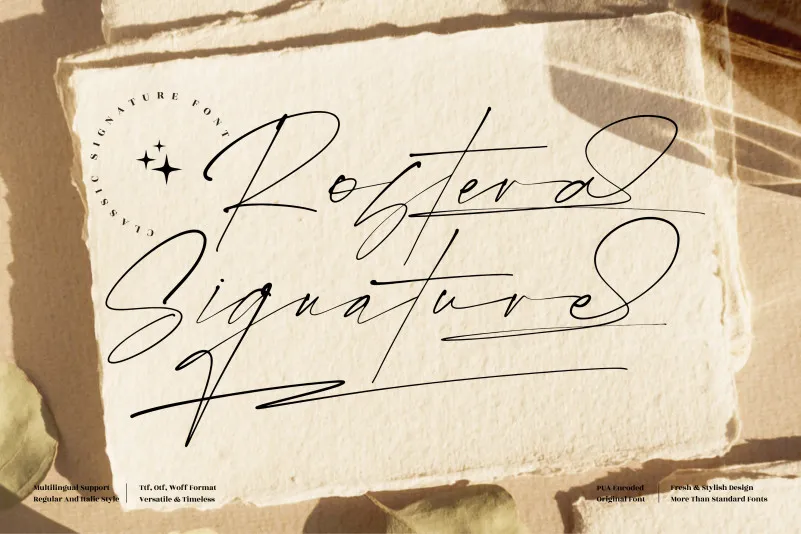
Rostera Signature Font – Download Grátis
A Rostera Signature Font é uma elegante tipografia script fina que traz a sofisticação necessária para criar cartões de convite de casamento surpreendentes, arte de papelaria inspiradora e postagens capturadoras nas redes sociais. Suave e requintada, esta fonte encaixa-se perfeitamente em qualquer projeto onde uma letra delicada é desejada. Com sua codificação PUA (Pictographic User Access), você pode explorar facilmente todos os incríveis caracteres e ligaturas que ela oferece. Seja para um evento de casamento especial ou apenas para personalizar suas próprias cartas, a Rostera Signature Font certamente será uma escolha inspiradora para seus projetos criativos em design de papelaria e comunicação visual.